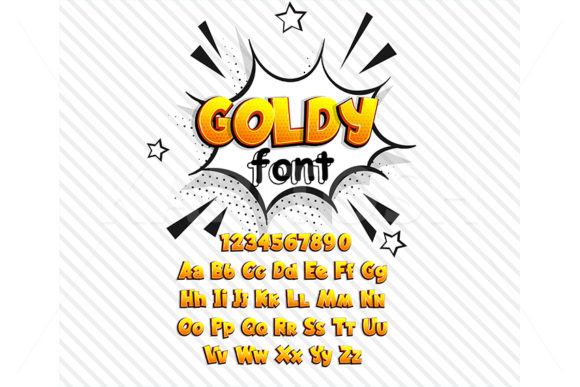
Yellow Lowercase Uppercase Comic Font
Se você está procurando a fonte perfeita para dar vida a projetos de quadrinhos, capas de super‑heróis ou qualquer arte pop‑art, Yellow Lowercase Uppercase Comic Font é a escolha ideal. Esta fonte combina estilo ousado, sombra em meia‑tom e balões de fala que transformam qualquer texto em uma explosão visual. A seguir, descubra por que designers, publicitários e criadores de conteúdo adoram esta tipografia.
- Alfabeto completo: letras minúsculas e maiúsculas em estilo comic, prontas para usar em títulos, diálogos e branding.
- Design em halftone com sombra que cria profundidade e dá aquele toque clássico de quadrinhos vintage.
- Balões de fala integrados: ideal para criar diálogos autênticos sem precisar de recursos externos.
Aplicações Ideais
- Design de interiores temáticos (murais, adesivos de parede).
- Campanhas publicitárias e peças de outdoor.
- Banners, posters e flyers de eventos.
- Impressões em vestuário, camisetas e bonés.
- Stickers, rótulos e embalagens criativas.
Por que Escolher Yellow Lowercase Uppercase Comic Font?
Esta fonte não é apenas um conjunto de letras; é um instrumento de storytelling visual. Seu estilo comic bold, aliado a sombras de halftone e balões de fala, oferece a autenticidade dos quadrinhos clássicos ao mesmo tempo que se adapta a projetos modernos de marketing e design. Além disso, por estar em vetor EPS, a qualidade permanece impecável em impressões de grande escala ou em uso digital.